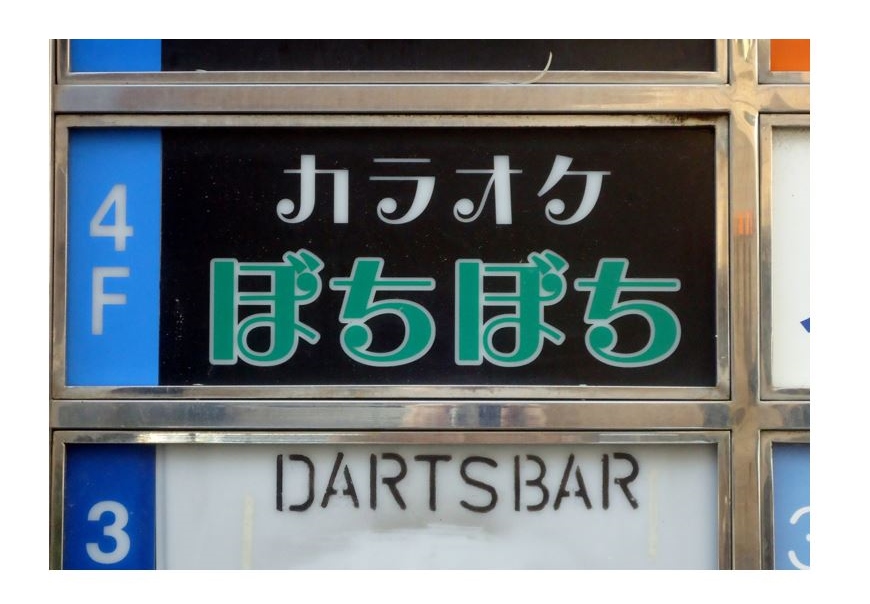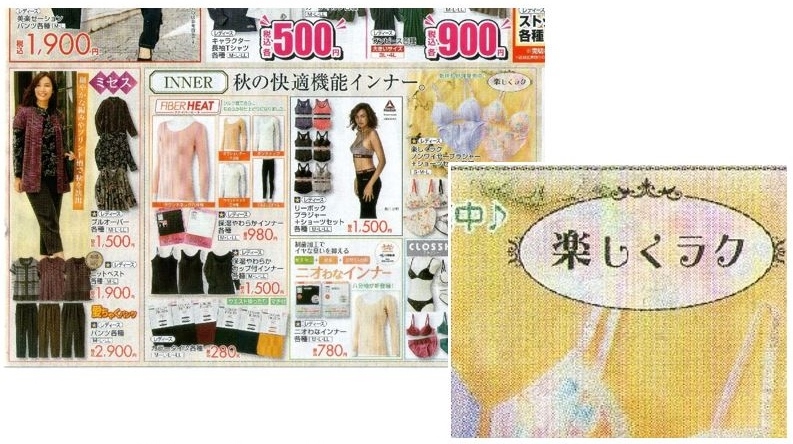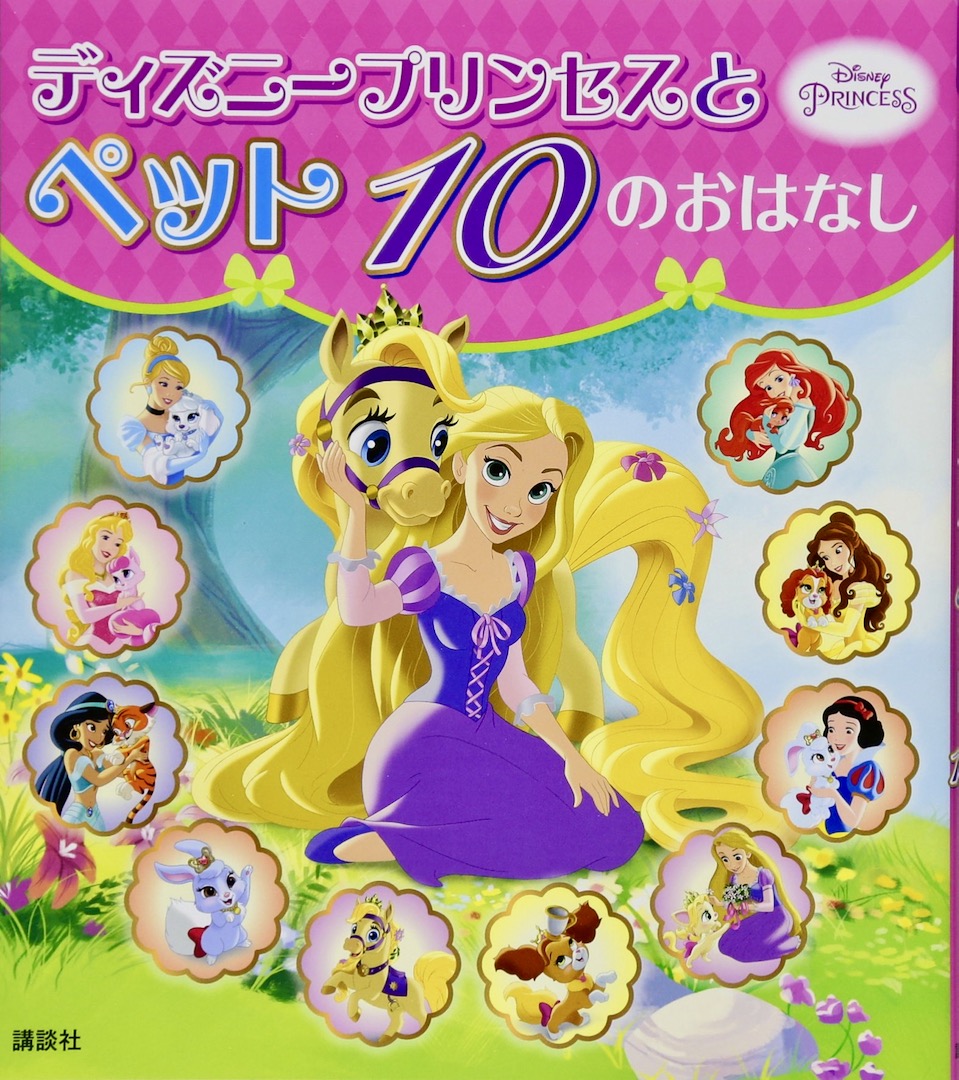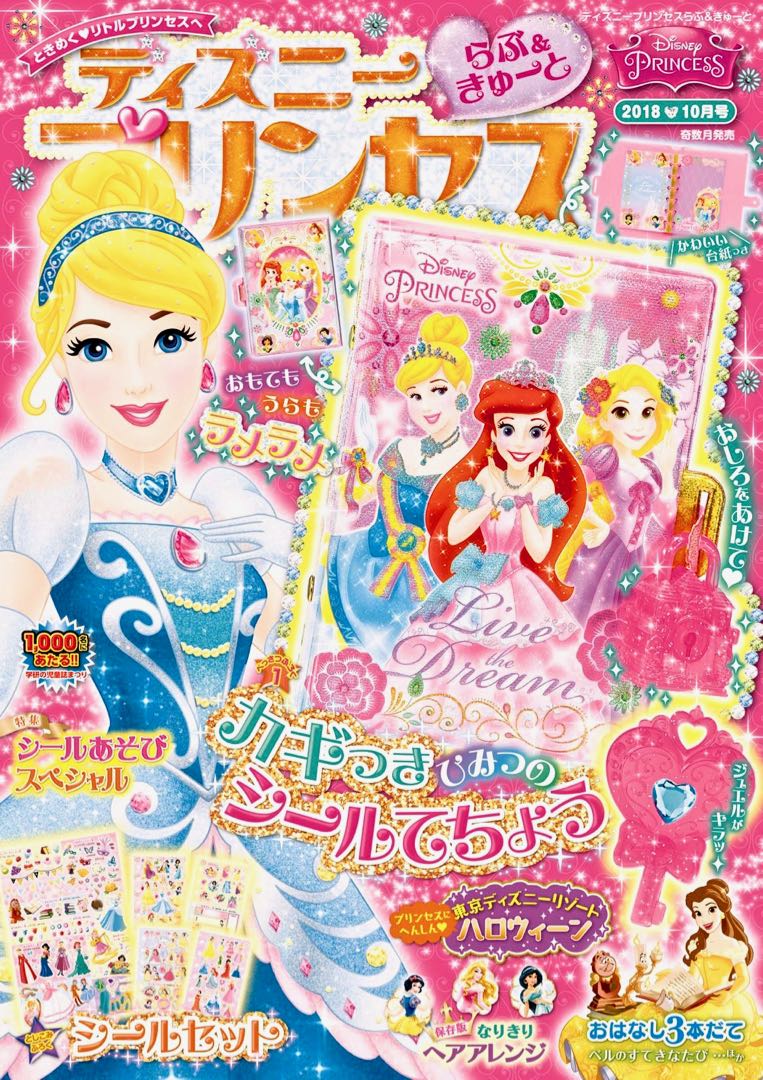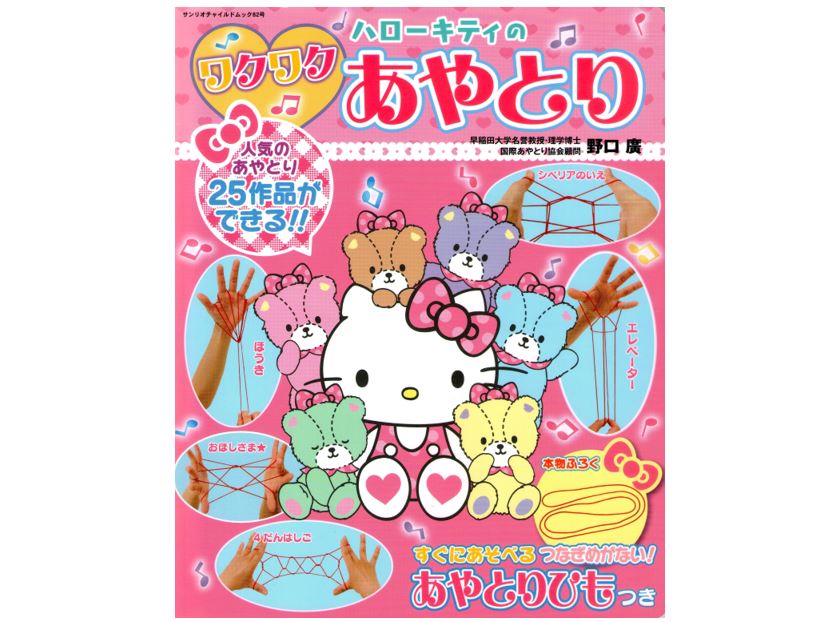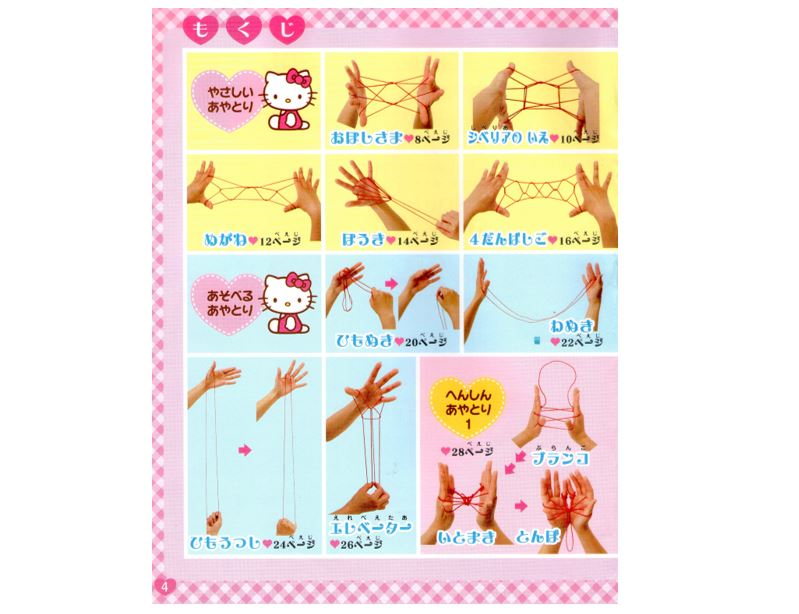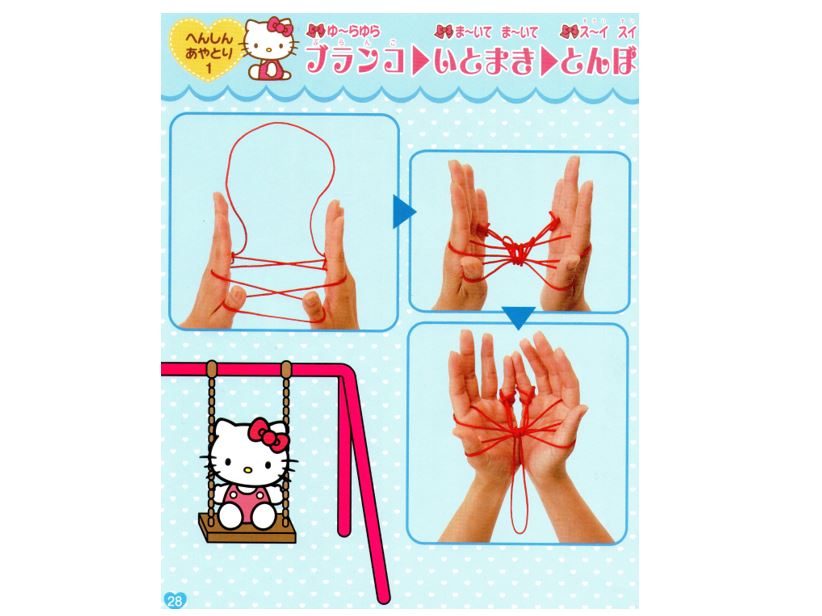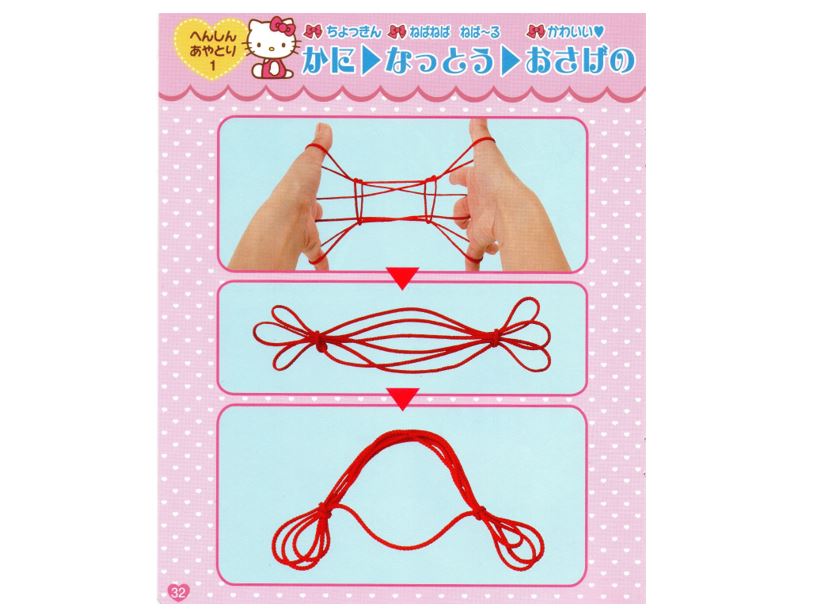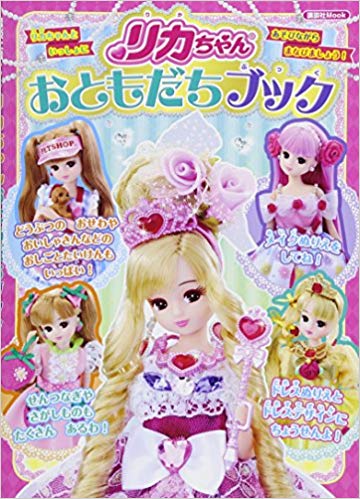
大阪市生野区のカラオケ居酒屋の看板です。
今日、自転車で3時間のフォント探しで見つけました。
サンリオのバーチャルタレント(バーチャルYouTuber)「となりの研究生マシマヒメコ。」の名前にえれがんとフォントが使われていました。
漢字の「研究生」の各文字にも、くるんとした加工がされています。
大阪市平野区、SSのバレンタイン向け商品の特設売り場、メッセージカードコーナーです。
バレンタインデーにも、このフォントは似合いますね!
埼玉県の通販会社ベルーナのカタログ「ベストアイテムコレクション」です。
一瞬「えれがんと平成明朝」かと思ったのですが、かな書体「えれがんと」との混植のようです。
まだ販売数が少ないので「えれがんと平成明朝」の使用例は、なかなか見つからないですね…。
今日平野区のSS玩具売り場で見つけました。
タカラトミーのリカちゃんシリーズのビューティハウスです。
パッケージにたくさん使われています。
リカちゃんとえれがんと書体は、お似合いですね。
旅行先(ハワイ)のお店のPOPでえれがんとを見かけました。
「香り爽やか!」の文字ですね。
一緒に使われているフォントを見た感じ、タイプラボで頒布されているえれがんと平成明朝じゃないかな?と思います(わかりませんけどね)。
海外なので日本と比べると日本語を見る機会は多くなく、あってもOS標準フォントなどが多かったので、まさかタイプラボフォントが見られるとは思わず、ウキウキ♪しました(笑)。
大阪市,市民生協おおさかパルコープ・大阪よどがわ市民生協のカタログ1月版です。
2ページと26ページの「今週のおすすめ」のページで同じ「カレー」の文字が使われています。
こちらが26ページです。
SNSにも上げましたが、プリキュア新シリーズのサイトでえれがんとが使われていました。
えれがんと平成明朝の無料頒布版かな?と。
(違っていたらスミマセン)
漢字がないのでなんとも言えませんが、わざわざ濁点を加えてますから、無料版でしょうね(笑)。
大阪市内に展開しているスーパーのチラシ。
ライセンスもの「えれがんと」との混植です。
チラシ全体の4分の1の該当部分。メィンタイトルとして大きく使用されています。
この書体は、クリスマスにぴったりですね。
大阪市平野区、SS書籍売り場で見つけた箱状の設置物です。
中に、特にアピールする書籍を入れています。